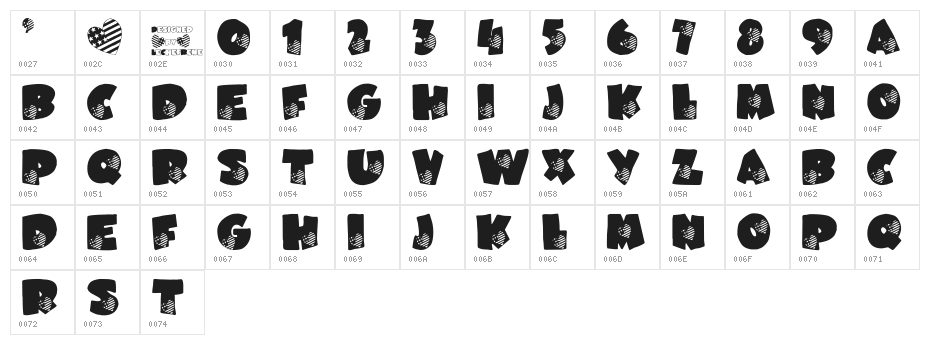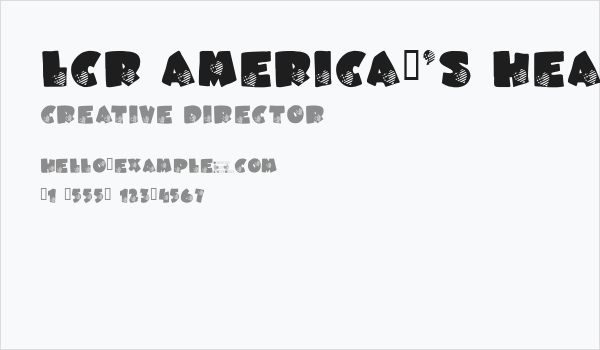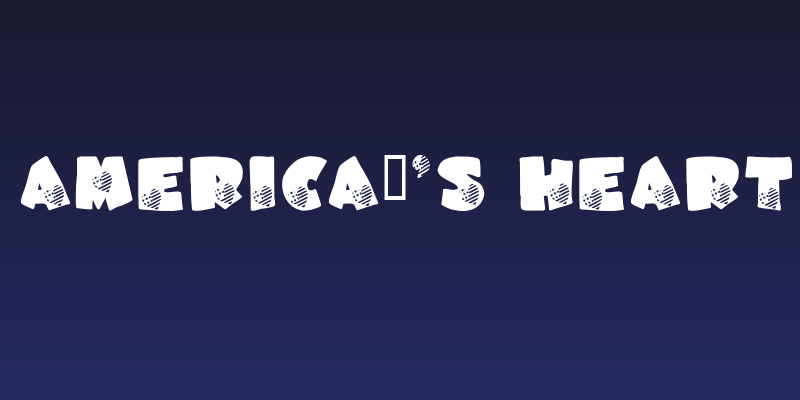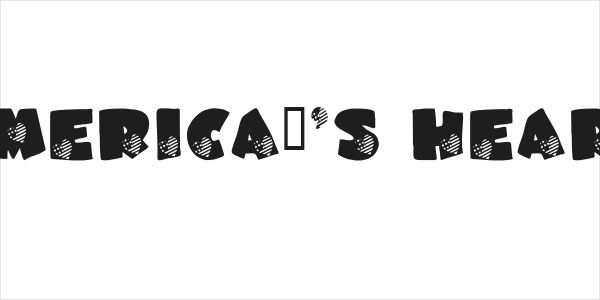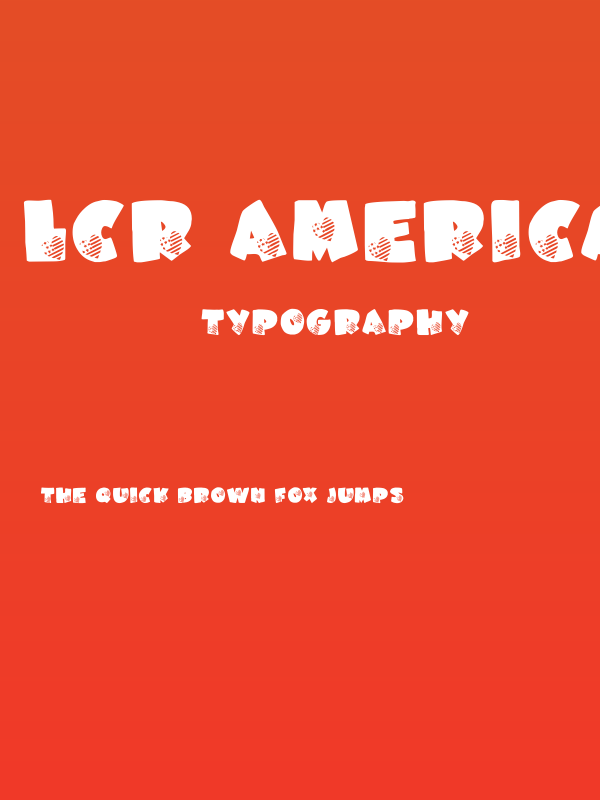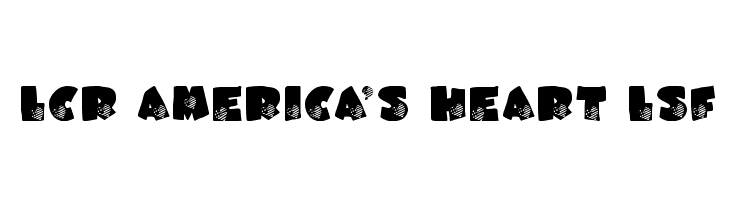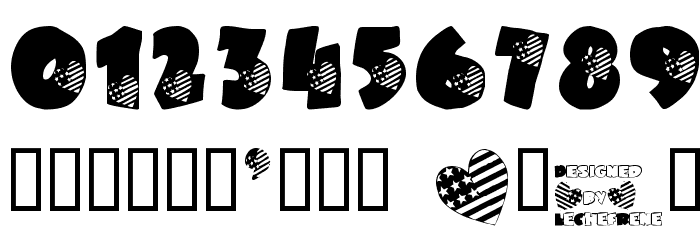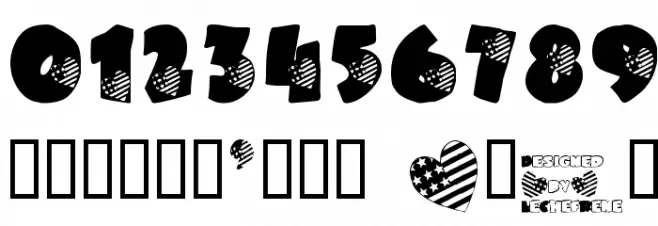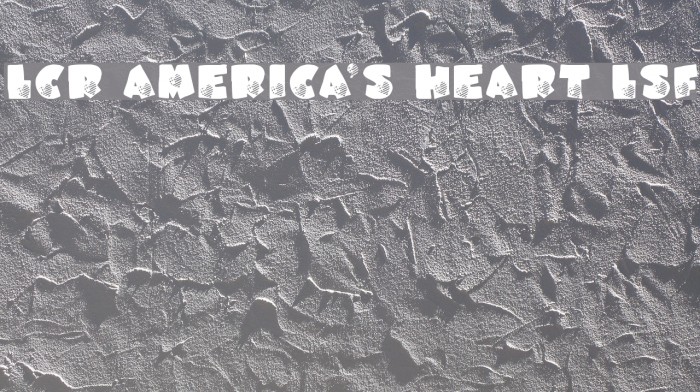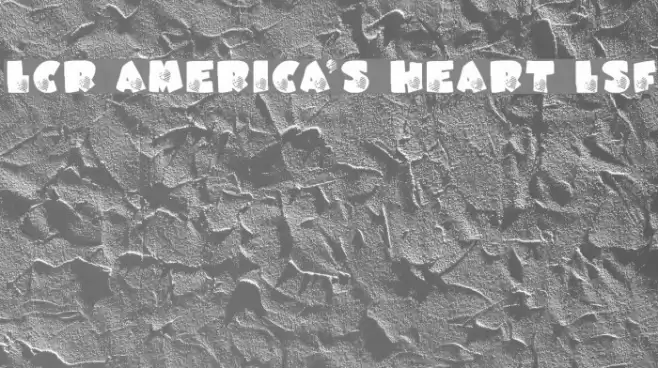
LCR America's Heart LSF Font
| Cas d'utilisation | Headlines, Posters, Banners |
| Projets proposés | Perfect for patriotic-themed posters, children's book covers, festive banners, and event invitations. |